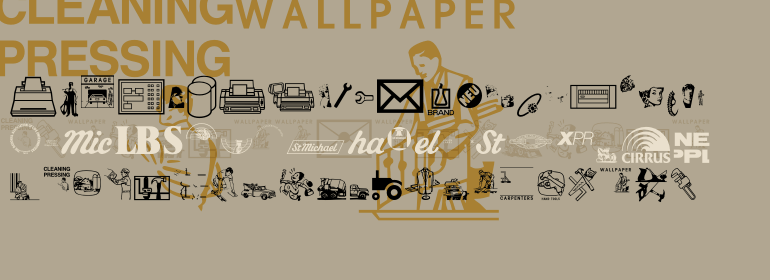
Business & Services
Business & Services,这款字体结构工整、笔画清晰,兼顾美观与易读性,适用于标题、正文、海报、包装、LOGO 等多种场景。字形优雅稳定,风格百搭耐看,适配日常排版与创意设计,让文字呈现更舒适、更具质感。Business & Services一笔一画,皆是细节,以均衡的比例、流畅的线条打造舒适视觉体验,字形端正大气,风格简约现代。无论是商业设计、品牌宣传还是日常排版,都能轻松驾驭,让文字更有格调与力量。Business & Services字体下载。